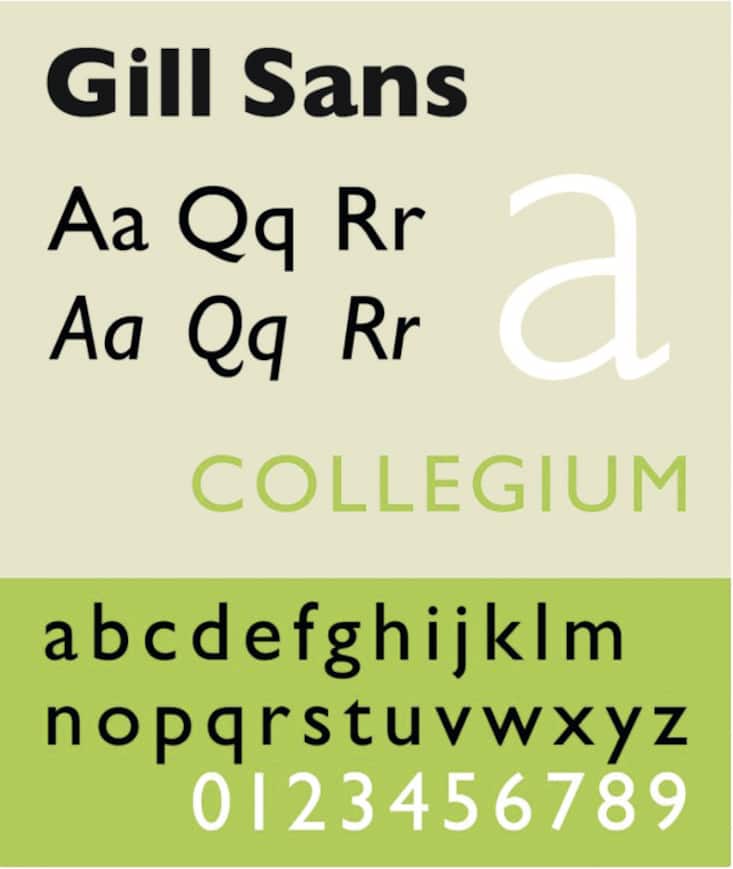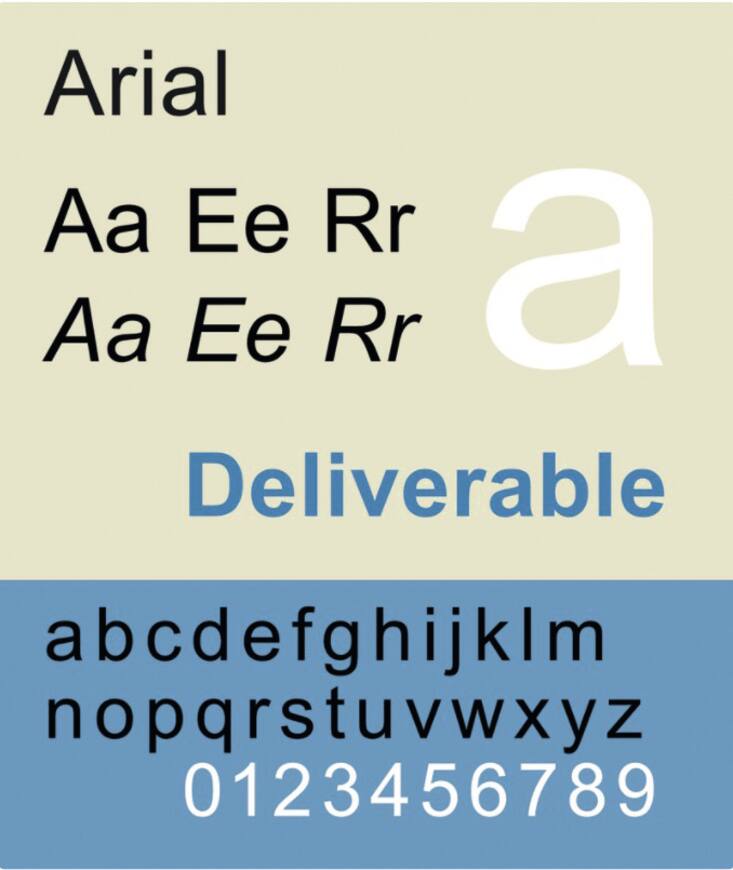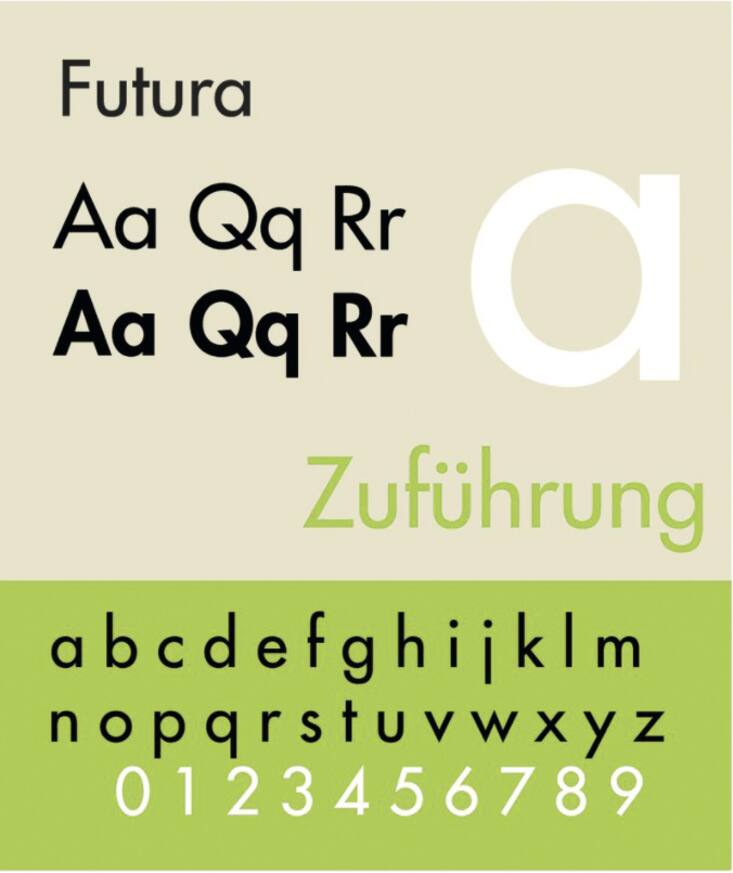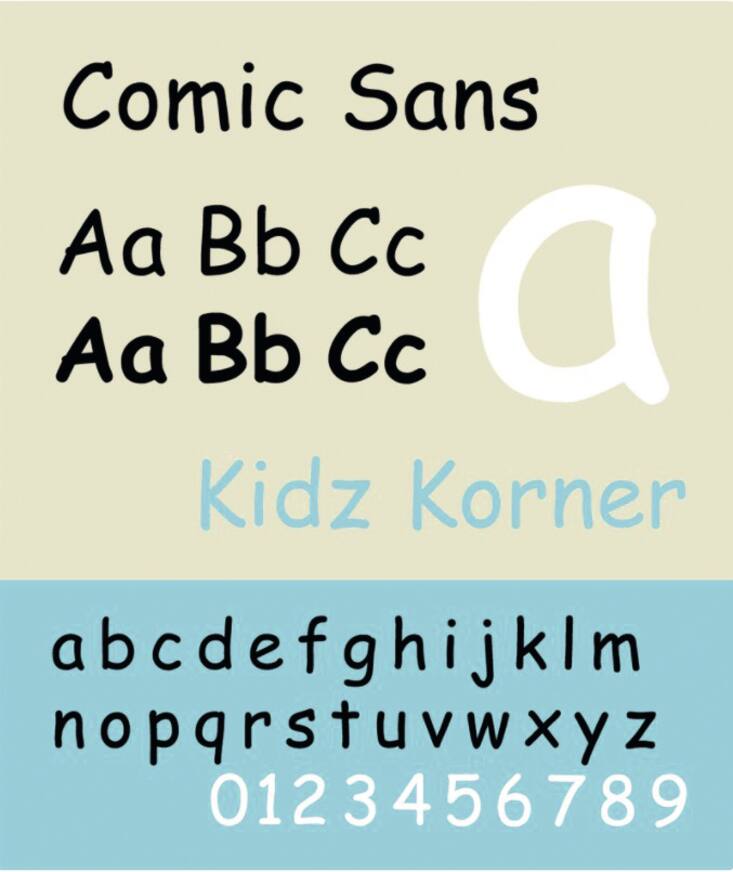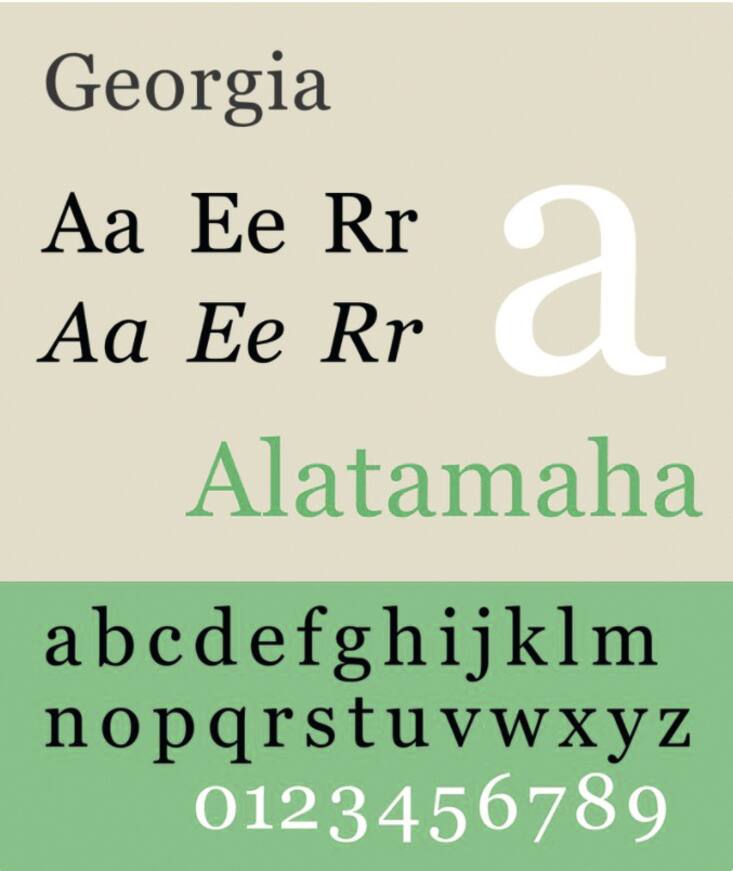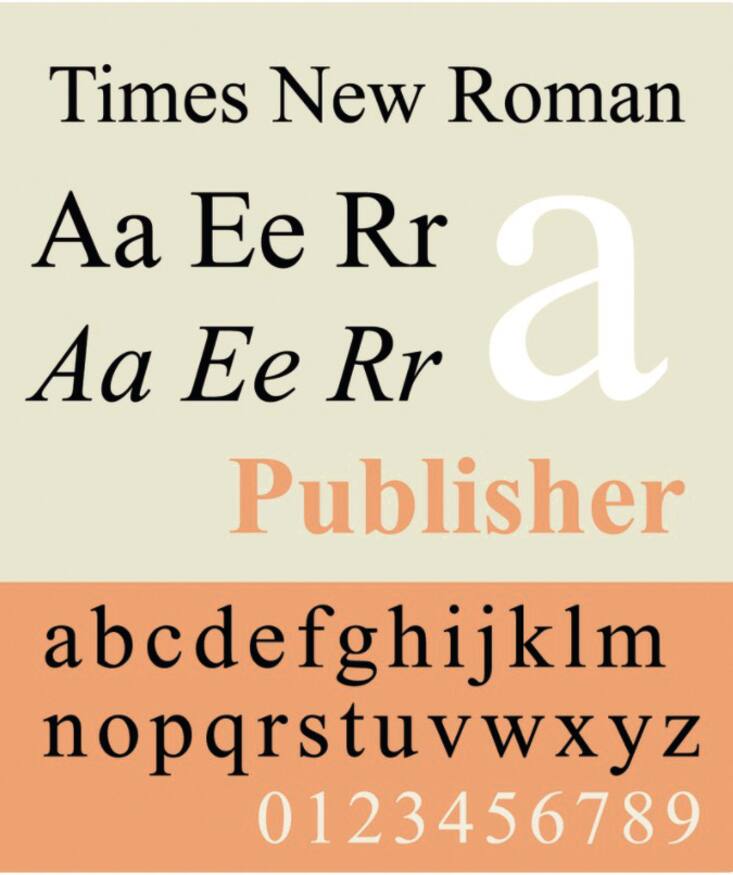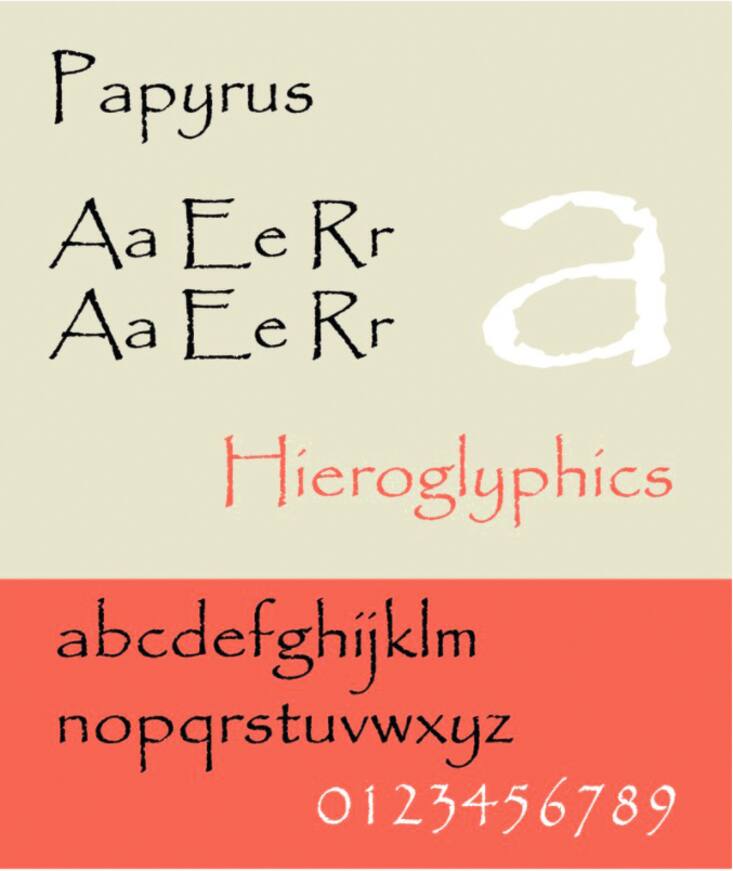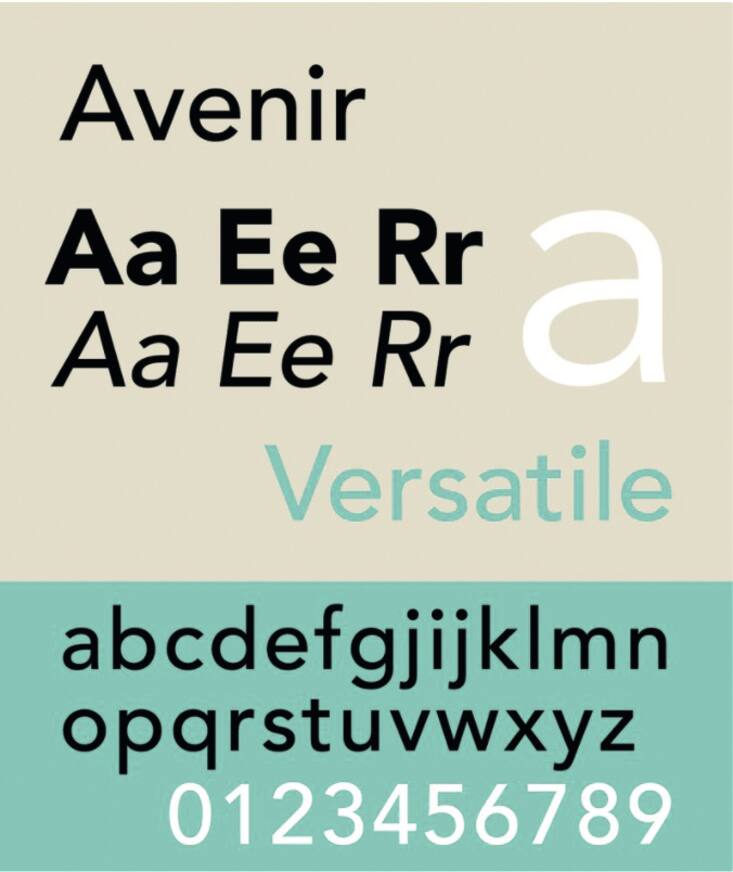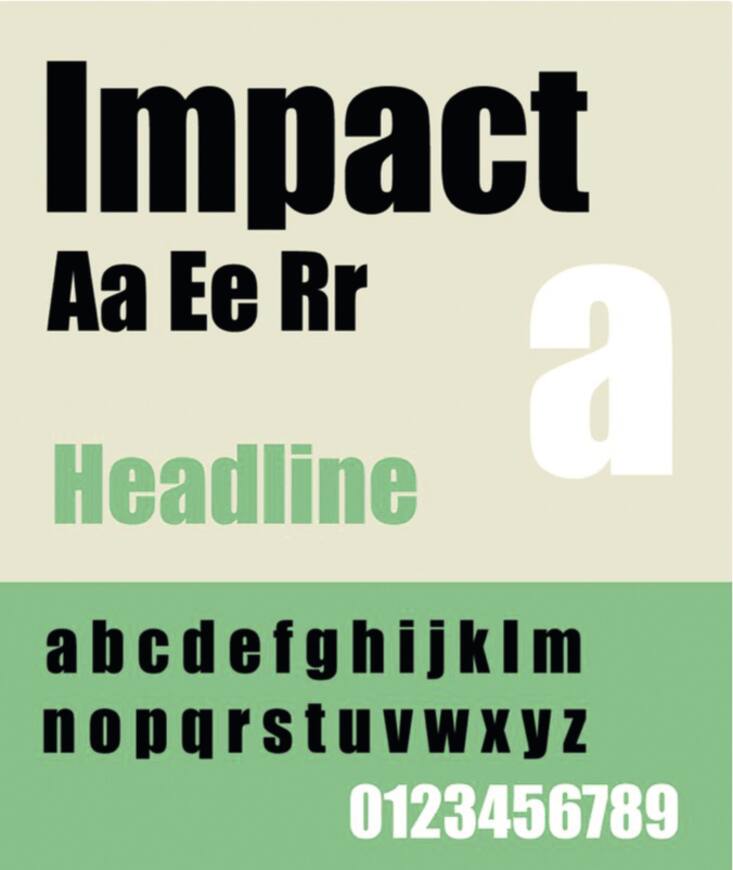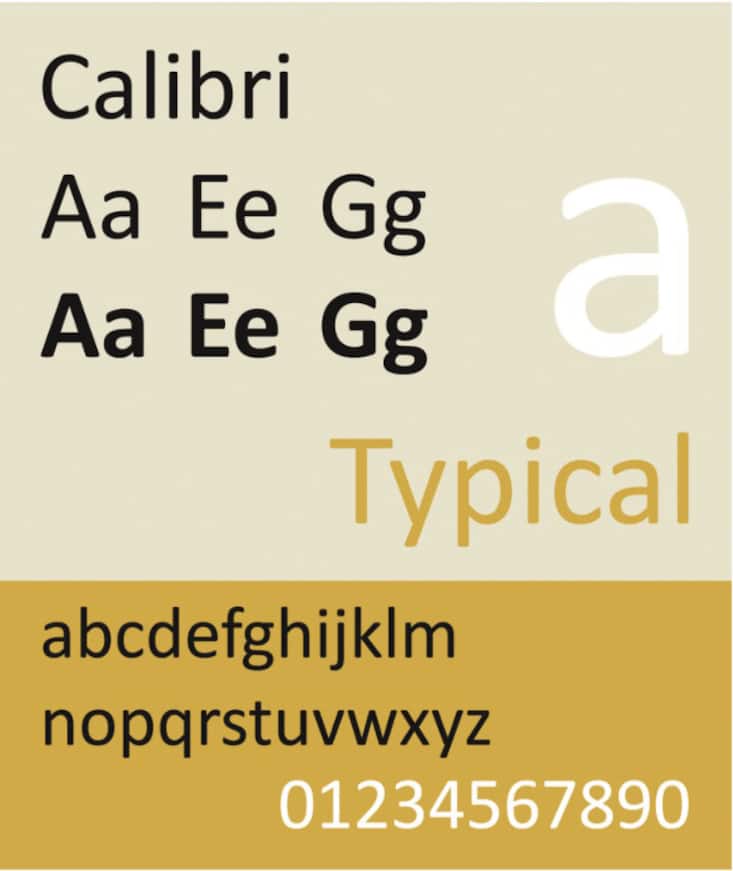
Viele neigen bei Lebensläufen und Bewerbungen dazu, möglichst gebräuchliche Schriftarten wie etwa Times New Roman zu wählen. Tun Sie das nicht und weichen Sie auf schöne, leicht lesbare und frische Varianten wie Garamond aus. Die moderne Version hat den Vorteil, dass Ihr Lebenslauf einen klassischen, polierten Look erhält. Wenn Sie Schwierigkeiten haben, Ihren Lebenslauf auf ein bis zwei Seiten zu komprimieren, kann Garamond Ihnen helfen, mehr Text auf einer Seite einzufügen, ohne die Lesbarkeit zu beeinträchtigen.
Gill Sans
Diese einfache, anspruchsvolle Schrift, die in den 1920er Jahren in England entwickelt wurde, wird Ihrem Lebenslauf einen klassischen und gleichzeitig modernen Look verleihen. Sie ist leicht lesbar, auch auf mobilem und PDF-Format sowie auf Bildschirmen, und erscheint nicht flimmernd oder als Belastung für das Auge. Besonders im englischsprachigen Raum hat sich diese Schriftart bei Bewerbungen und Lebensläufen durchgesetzt, die BBC verwendet sie standardmässig. Sie finden diese Schriftart in Mac OS X und in einigen Microsoft-Programmen als Gill Sans MT.
Cambria
Lato ist eine serifenlose Schrift, die ursprünglich für den Gebrauch in Firmen entwickelt wurde. Der Designer der Schrift beschreibt Lato als «ernsthaft, aber freundlich» – und tatsächlich ist sie perfekt für Lebensläufe. Es gibt eine grosse Auswahl an Varianten und Stilen der Schrift. Da jedoch die Varianten Hairline, Thin und Light bei kleinen Grössen sehr schwer zu lesen sind, verwenden Sie besser die Standardvariante. Die Schriftart steht zum Download bereit (kostenlos für den persönlichen und gewerblichen Gebrauch). Auch Google Fonts führt die Schriftart.
Obwohl sie seit 2007 die Standard-Schriftart von Microsoft Word ist, wird Calibri immer noch nicht so oft verwendet wie Arial, die aus diesem Grund auf unserer «Worst»-Liste steht. Denn grundsätzlich sollten Sie zu häufig verwendete Schriftarten bei Ihren Bewerbungsunterlagen vermeiden. Die Schriftart Calibri hat viele nützliche Vorteile; die Karriereexpertin Donna Svei weist etwa darauf hin, dass die Eingabe von Calibri in einer Grösse von 12 Punkten etwa 500 bis 750 Wörter ergibt, die ideale Länge eines zweiseitigen Lebenslaufs – mehr wird Ihr Recruiter auch kaum lesen.
Constantia
Ein weiteres gut nutzbares Beispiel aus der Clear Type Font Collection von Microsoft: Constantia. Die runderen Buchstabenformen lassen sie freundlicher und weniger muffig aussehen als viele Serifenschriften (Serifen sind dünne Linien, die einen Buchstaben entgegen seiner Hauptrichtung abschliessen; achten Sie etwa auf die dünne Linie unter einem «F»). Die Schriftart eignet sich für die Verwendung sowohl auf Bildschirmen, ob Handy oder PC, und in gedruckter Form.
Lato
Lato ist eine serifenlose Schrift, die ursprünglich für den Gebrauch in Firmen entwickelt wurde. Der Designer der Schrift beschreibt Lato als «ernsthaft, aber freundlich» – und tatsächlich ist sie perfekt für Lebensläufe. Es gibt eine grosse Auswahl an Varianten und Stilen der Schrift. Da jedoch die Varianten Hairline, Thin und Light bei kleinen Grössen sehr schwer zu lesen sind, verwenden Sie besser die Standardvariante. Die Schriftart steht zum Download bereit (kostenlos für den persönlichen und gewerblichen Gebrauch). Auch Google Fonts führt die Schriftart.
Didot
Didot ist eine unverwechselbare Schrift mit gehobener Optik (entwickelt wurde sie in Paris). Diese elegante Schrift kann Ihrem Lebenslauf etwas mehr Stil verleihen und scheint besonders in der Modebranche und der Fotografen- und Fotografinnenszene beliebt zu sein. Ihre zarten Serifen zeigen sich jedoch am deutlichsten bei grösseren Grössen, sodass Sie Didot am besten für Überschriften und nicht für Textblöcke nutzen sollten. Wer seinen Namen über den CV setzen will, sollte auf Didot zurückgreifen.
Helvetica
Diese Schweizer Sans-Serif-Schrift wird von vielen Typografen als die Königin der Schriften angesehen. Sie hat sogar einen eigenen Dokumentarfilm. Dank ihrer modernen, klaren Linienführung und Klarheit wird die Helvetica in allen Bereichen eingesetzt, von Firmenlogos (BMW, American Airlines, Microsoft) bis hin zu den U-Bahn-Schildern von New York City. Um Ihrem Lebenslauf ein sauberes und zeitgemässes Aussehen zu verleihen, das immer noch professionell ist, probieren Sie Helvetica. Im Mac-Betriebssystem ist die Schrift enthalten. Im Windows-System muss man sie kaufen.
Georgia
Georgia ist eine weitere Alternative zu Times New Roman. Diese Serifenschrift hat Buchstabenformen mit dickeren Strichen, die auch bei kleinen Schriftgrössen eine gute Lesbarkeit ermöglichen. Da die Schrift speziell für die Nutzung auf Computermonitoren und mit dem Ziel, möglichst viel Übersichtlichkeit herzustellen, entwickelt wurde, eignet sie sich perfekt dafür, Ihre Dokumente auf Monitoren und digitalen Darstellungsformaten auszuspielen. Wer den CV per PDF sendet, kommt an Georgia kaum vorbei.
Avenir
Diese vielseitige serifenlose Schrift hat ein sehr sauberes, klares Erscheinungsbild, das jedem Lebenslauf ein frisches und seriöses Aussehen verleiht. Es gibt mehrere Schriftvarianten, die Sie verwenden können, um die verschiedenen Abschnitte oder Kapitel Ihres Lebenslaufs zu unterscheiden, aber Sie sollten wahrscheinlich die Varianten Book und Light sowie alle komprimierten Versionen vermeiden – sie können schwer zu lesen sein. Avenir Next ist eine weitere gute Option; sie wurde als Nachfolgerin von Avenir veröffentlicht, um die Bildschirmfunktionen der Schrift zu verbessern.
Fakten zum Thema
72 grosse internationale Firmen nutzen die Schriftart Helvetica im Firmenlogo. Darunter Fendi, Bayer, Kappa und American Airlines. 1927 ist das Jahr, in dem Futura entwickelt wurde – eine der erfolgreichsten Schriften für Firmenlogos, darunter die von Fedex und Swissair. 2005 entstand Proxima Nova, die von vielen Webfirmen als Schriftart für das Logo verwendet wurde, darunter Spotify und Twitter